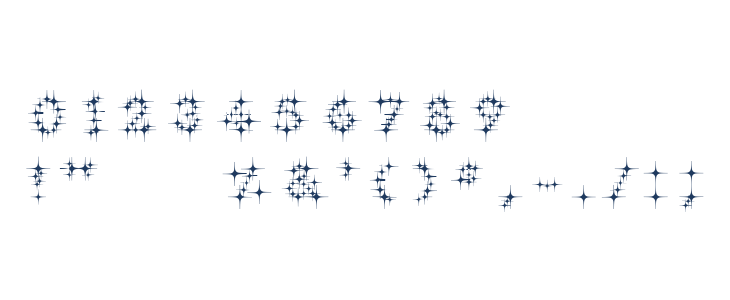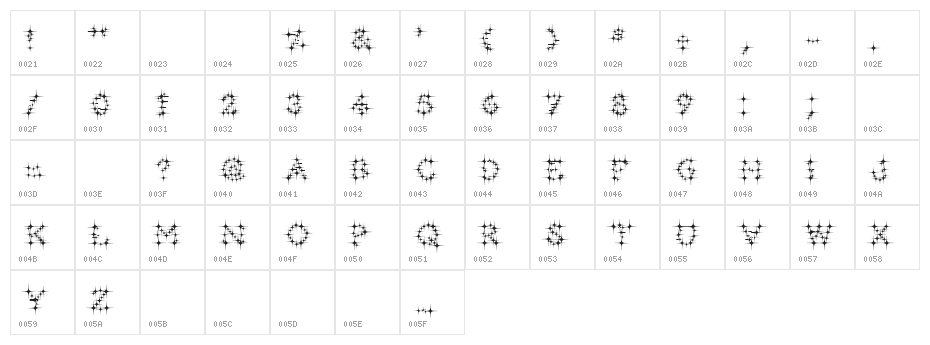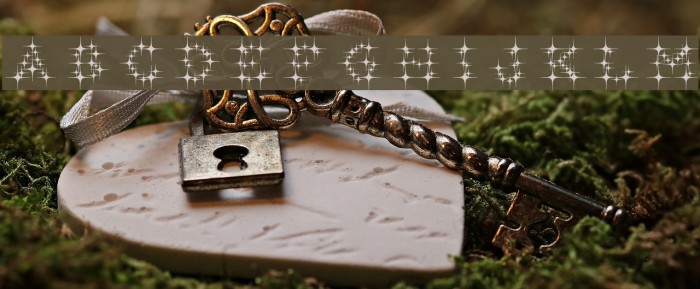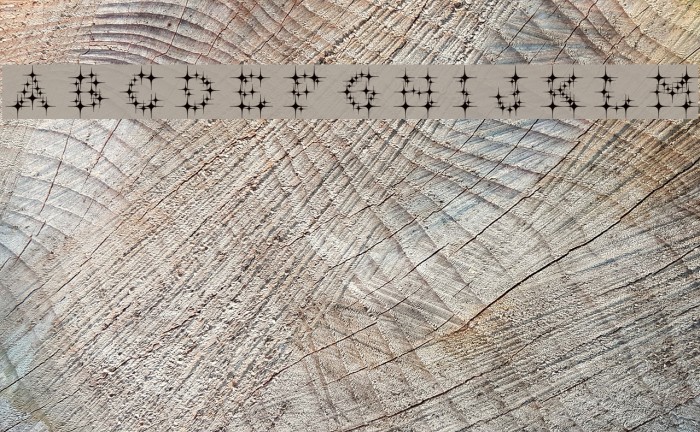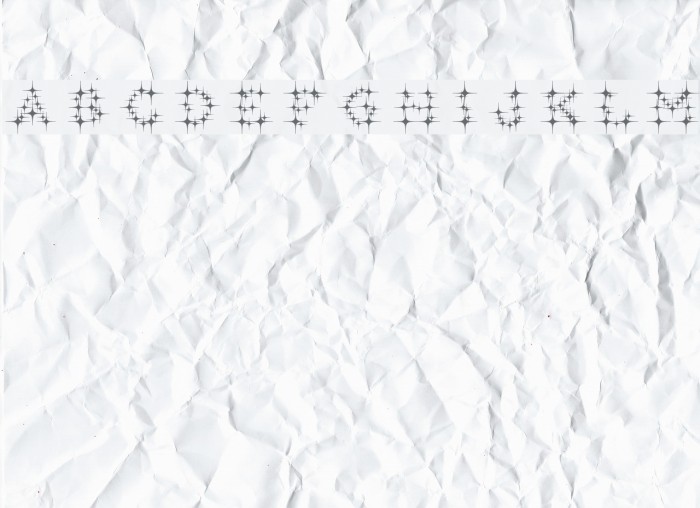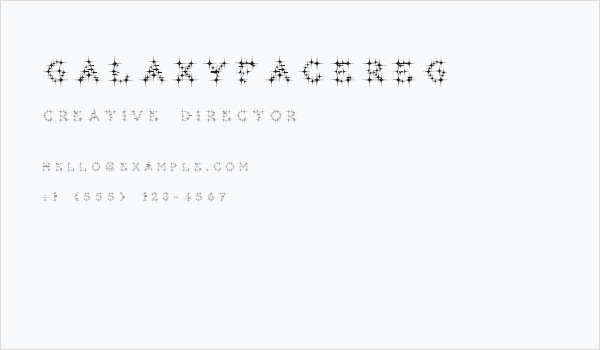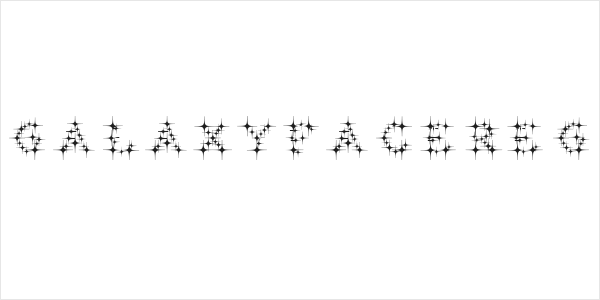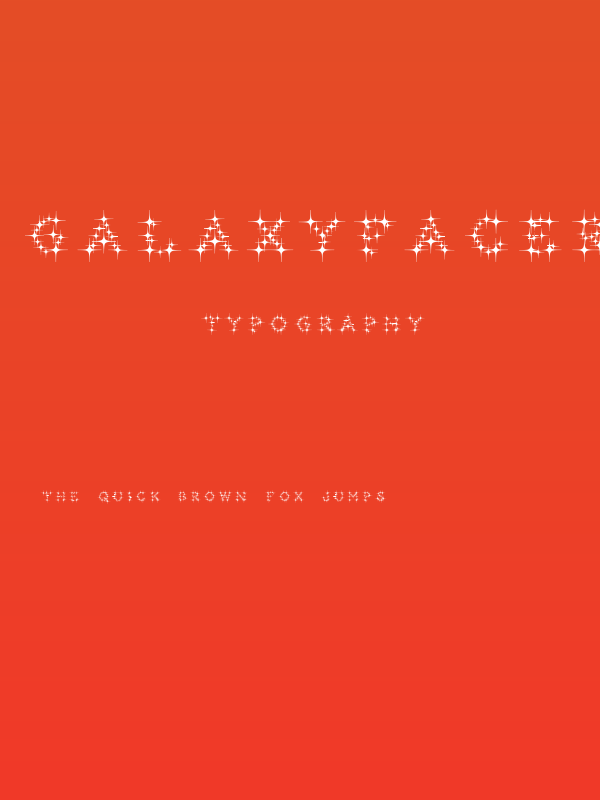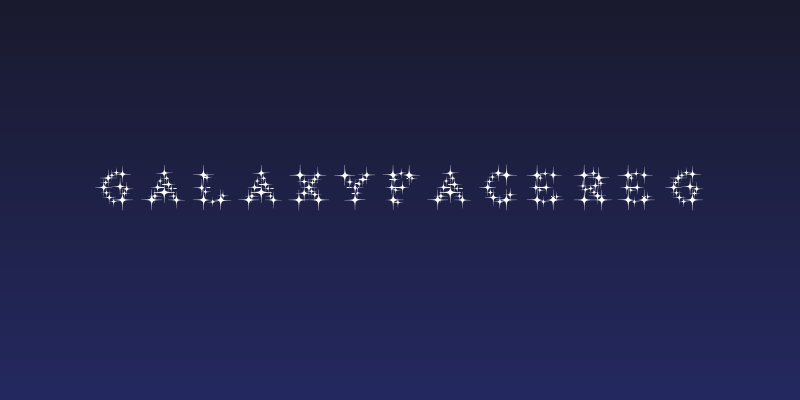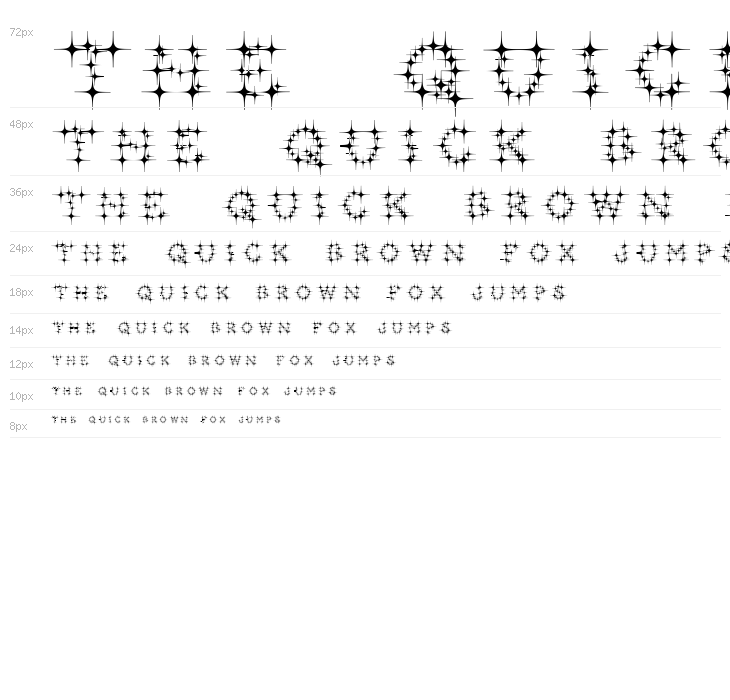
GalaxyfaceReg Font
| Anwendungsfall | Logos, Headlines, Posters |
| Vorgeschlagene Projekte | Ideal for projects that require a cosmic or fantasy theme, such as book covers, posters, or event invitations. |